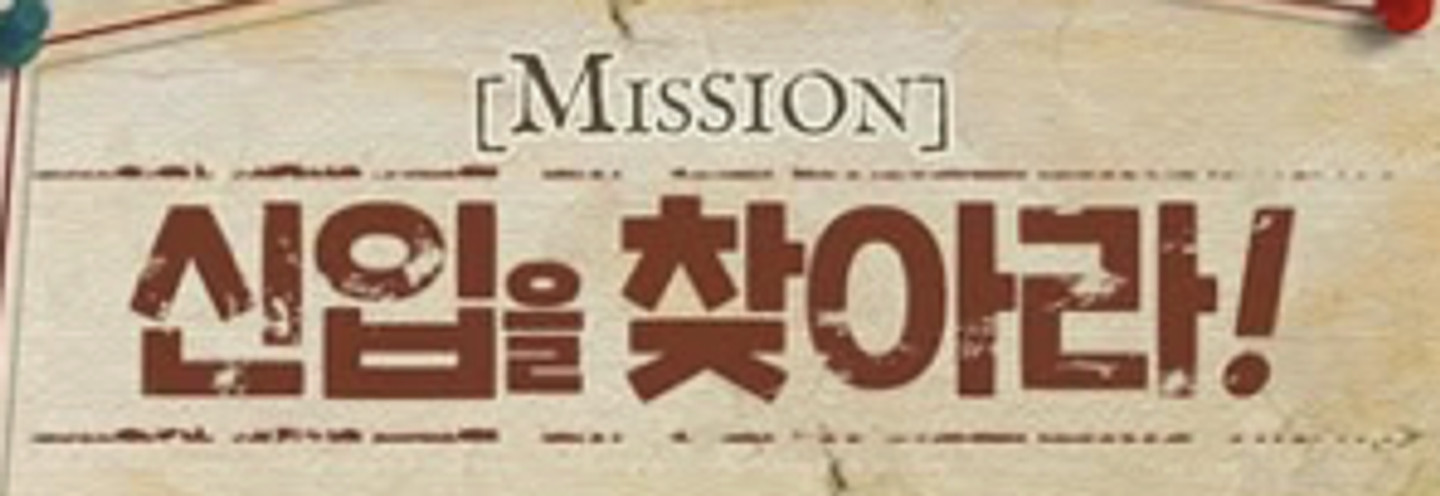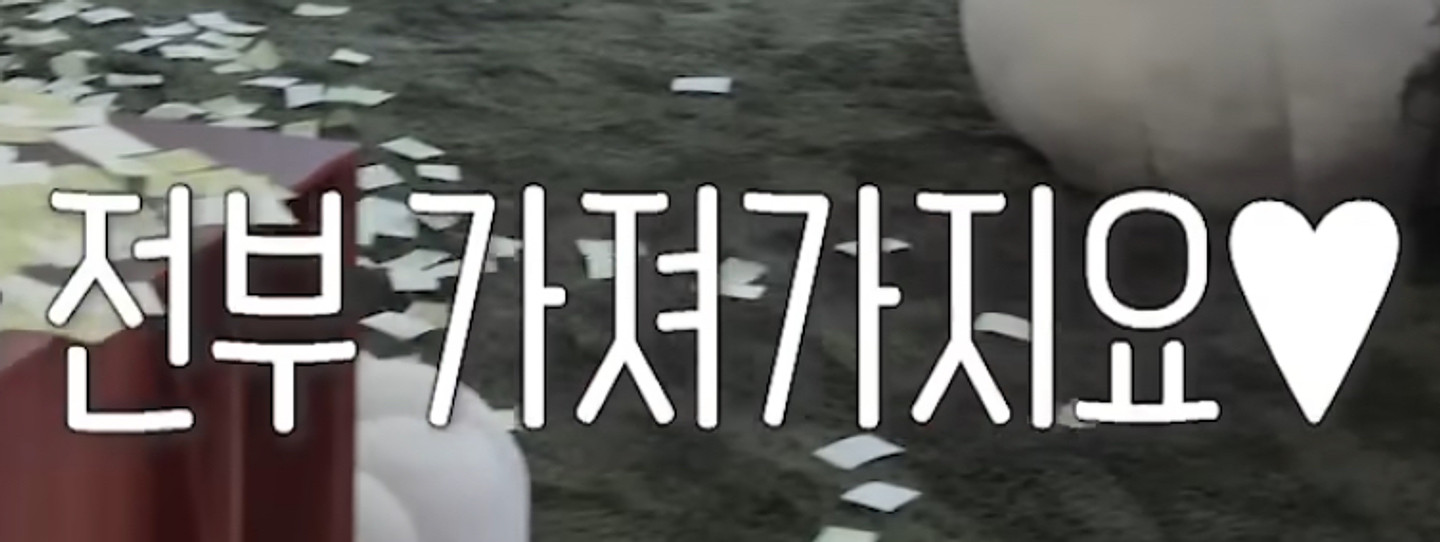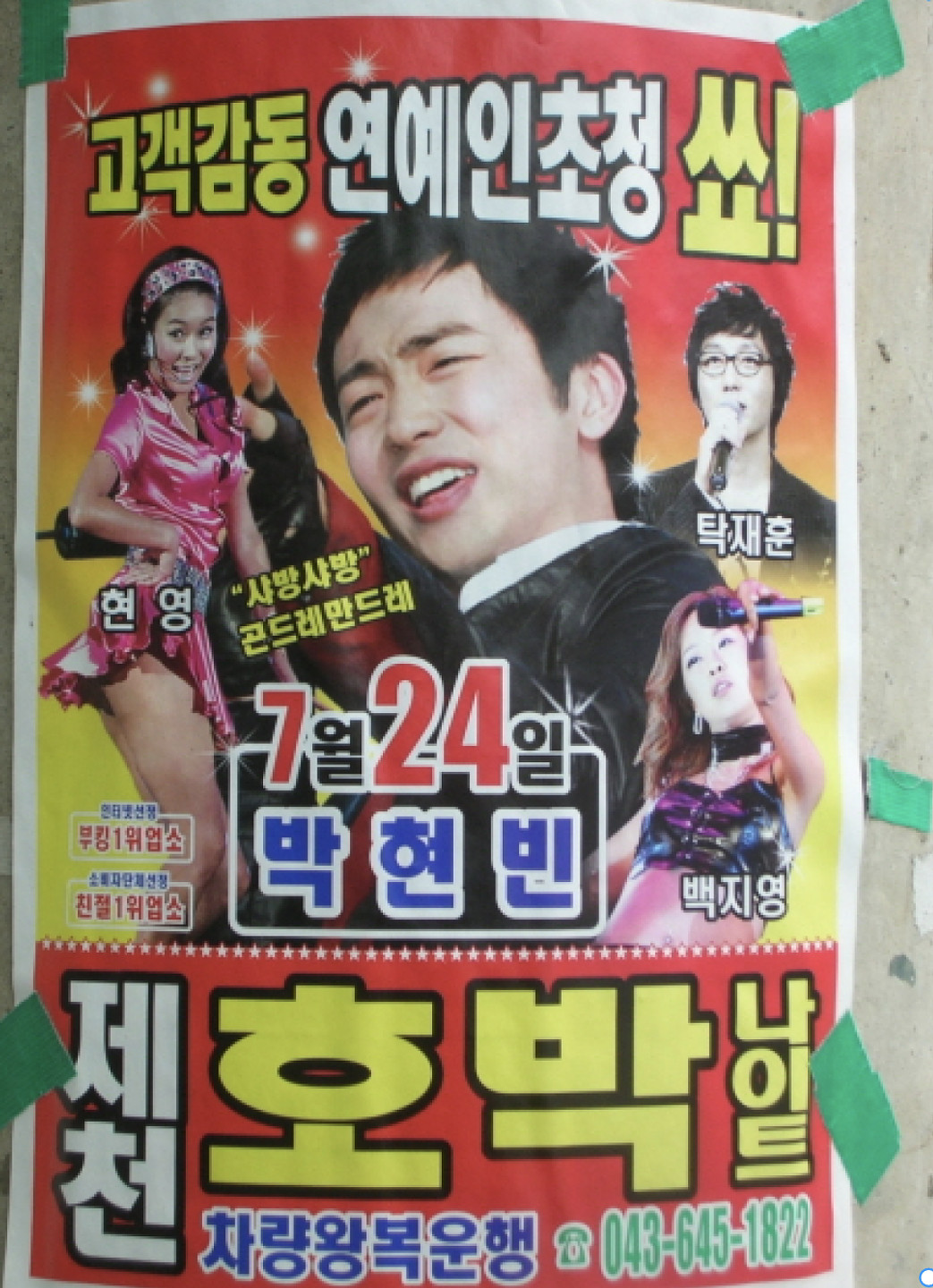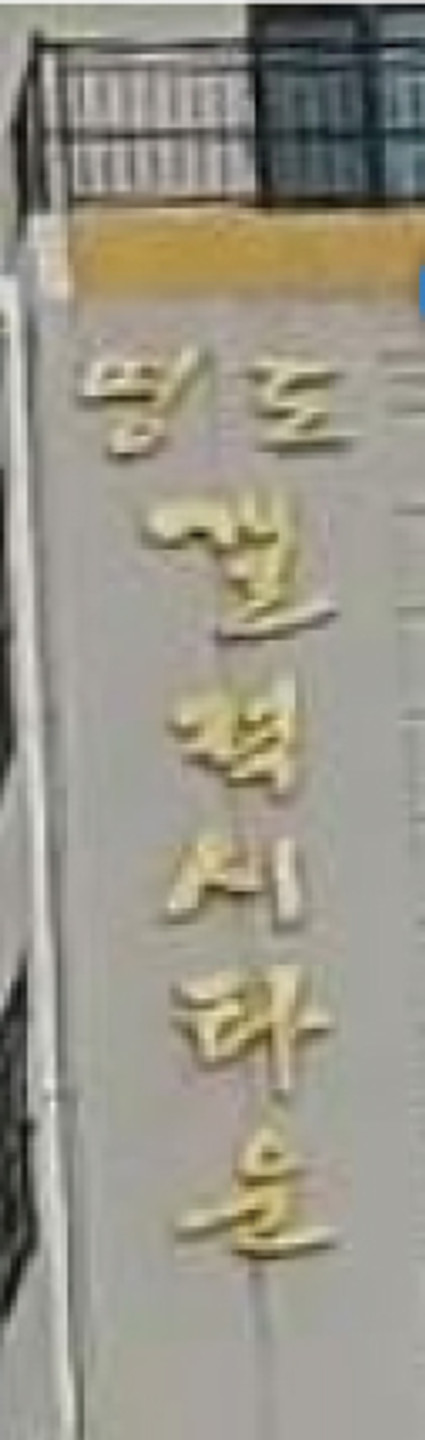
이 폰트 알려주세요!
답변 잘 받았습니다. 대댓글쓰는곳이없는거같아서요 캡쳐한뒤 다시 말씀이어서 드립니다 .,ㅎㅎ추천해주신 Soul 커피브레이크, Soul 율곡, Soul 데스페라도도 확인해봤는데 제가 원하는 것보다 획이 조금 가늘고, 구독형이라 장기간 반복해서 사용하기에는 부담스럽더라고요. 제가 찾는 폰트는 글자가 굵고 통통하면서도 손으로 쓴 것처럼 불규칙하고, 붓의 거친 결이나 긁히고 벗겨진 느낌이 있는 한글 붓글씨입니다. 구독형보다는 상업용 유튜브 썸네일에 사용할 수 있는 무료폰트나, 한 번 구매하면 계속 사용할 수 있는 유료폰트가 있으면 여러 개 추천 부탁드립니다. 현재 눈누에서 찾아본 폰트 중에는 그리운 경찰감성체, 정선아리랑체, 눈누마켓의 HCL 둥글납작펜을 후보로 생각하고 있습니다. 이 중 한 가지를 사용해서 외주 제작자에게 After Effects 작업을 맡기고, 완성된 MOGRT를 받아 제가 Premiere Pro에서 제목만 바꿔가며 유튜브 썸네일에 계속 사용하고 싶은데요. 이런 경우 각 폰트마다 제가 구매하거나 다운로드한 폰트를 외주 제작자가 작업에 사용할 수 있는지, 아니면 제작자도 별도의 라이선스나 구매가 필요한지 궁금합니다. 무료폰트라면 저와 제작자가 각자 공식 페이지에서 다운로드해 설치하면 되는지도 알고 싶습니다. 또한 완성된 MOGRT에 폰트 파일 자체는 포함하지 않고, 제가 제 컴퓨터에 폰트를 따로 설치한 상태에서 문구만 반복해서 바꿔 사용하는 방식이라면 상업적으로 계속 사용해도 괜찮은지도 확인 부탁드립니다.
안녕하세요. 상업용 유튜브 썸네일 제목에 반복 사용할 한글 붓글씨 폰트를 찾고 있습니다. 첨부한 이미지왼쪽에 조선힙합채널처럼 자연스럽고 불규칙한 붓글씨 느낌을 원합니다. 획이 힘 있고 손으로 쓴 듯한 분위기이면서, 오른쪽 쇼츠 이미지처럼 글자가 굵고 통통하며 내부에 거친 긁힘·벗겨짐 질감이 있는 폰트를 찾고 있습니다. 특정 채널의 폰트를 그대로 복제하려는 것은 아니며, 비슷한 특징을 가진 다른 폰트를 찾고 싶습니다. ‘210 오늘은 Bold’도 확인했지만 제가 원하는 것보다 획이 다소 가늘고 날렵하게 느껴졌습니다. 이보다 굵고 힘 있는 붓글씨 또는 캘리그래피 폰트가 있다면 유료 폰트를 포함하여 추천 부탁드립니다. 추천 폰트에 대해서도 아래 내용을 함께 알고 싶습니다. 1. 유튜브 썸네일 및 영상에 상업적으로 사용할 수 있는지 2. 낱개로 영구 구매할 수 있는지 또는 구독이 필요한지 3. After Effects로 MOGRT 템플릿을 제작한 후 Premiere Pro에서 반복 사용해도 되는지 4. 외주 제작자와 작업할 경우 각자 별도의 폰트 이용권이 필요한지 5. 구독 종료 후 기존에 제작한 영상·썸네일을 계속 게시할 수 있는지 가능하다면 첨부 이미지와 가까운 후보를 여러 개 추천해주시면 감사하겠습니다.
폰트 질문드려요
알고싶어요ㅠㅠ
이 폰트 알수 있을까요?
이 폰트를 찾고잇어요
궁금합니다!!!
이 글씨체 뭘까요?
폰트좀 알려주세요 ㅠ
궁금합니다 ㅠㅠ
이 폰트 이름
알려주세요 감사합니다ㅠ
글씨체 궁금해요
글씨체 찾아주세요ㅠ
손글씨같은 느낌이에요